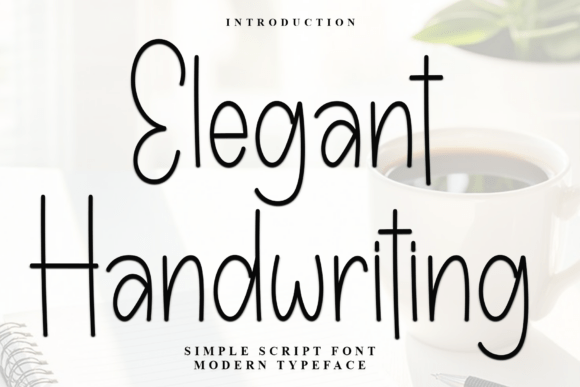
Elegant Handwriting
Jika Anda mencari aset berkualitas tinggi seperti Elegant Handwriting, paket premium ini adalah pilihan fantastis untuk proyek kreatif Anda.
Baik Anda membuat produk POD (Print on Demand), undangan pernikahan, atau grafis media sosial, Elegant Handwriting adalah pilihan yang sangat ideal.